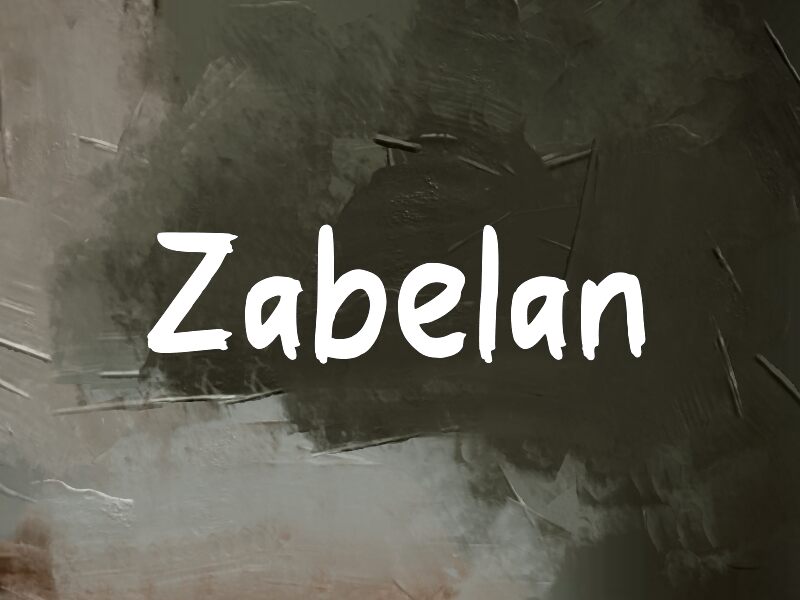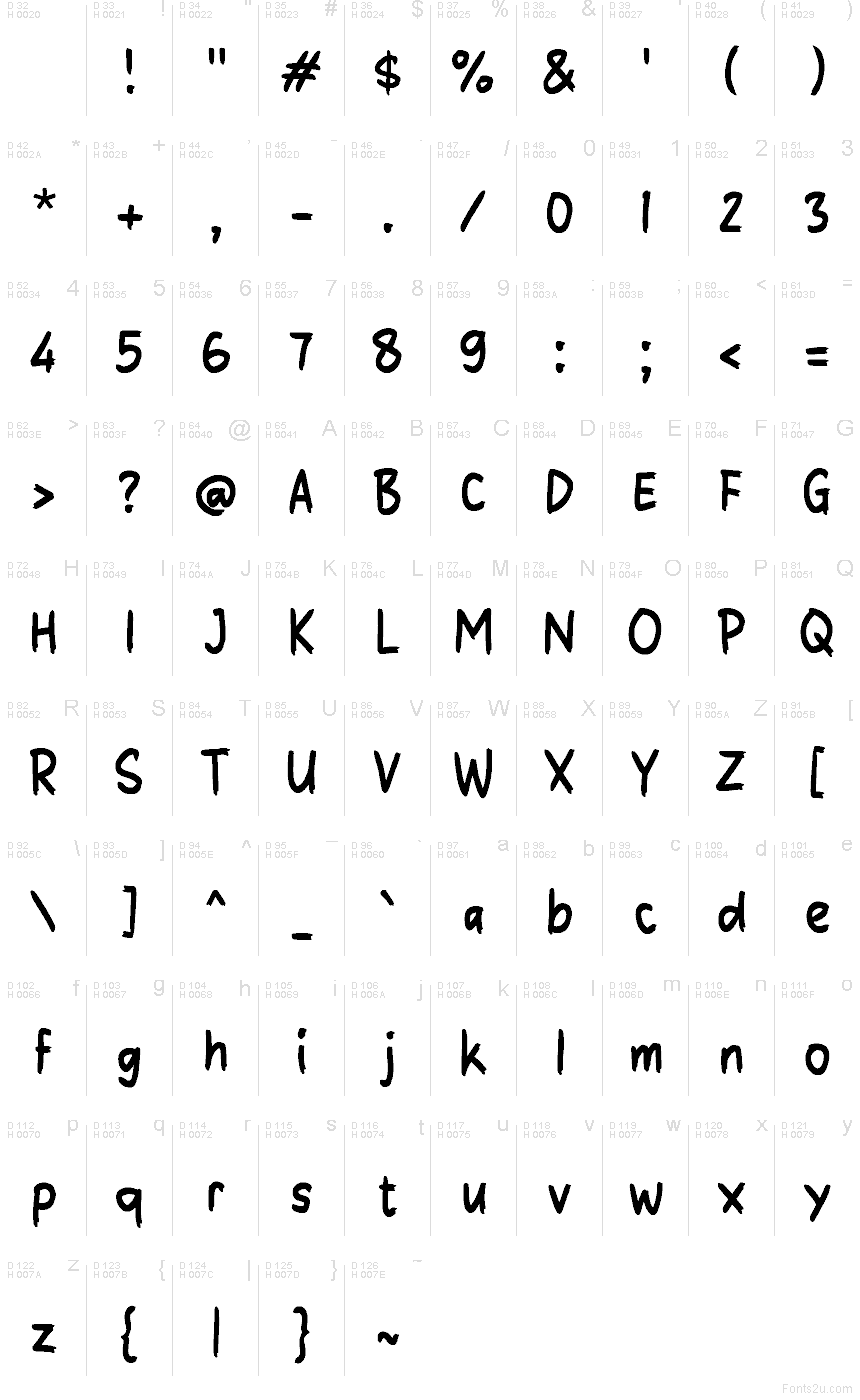
Zabelan
Zabelan od Wep je bezplatný brush font definovaný širokými ťahmi a rýchlym, vzpriameným rytmom. Písmená si zachovávajú ručne robený švih, s mierne nepravidelnými okrajmi a úzkymi spojmi, vďaka čomu pôsobia skôr ako nápis fixkou než ako uhladené písmo.
Táto autentická maliarska textúra dodáva krátkym titulkom na plagátoch, obaloch albumov, streetwearovej grafike, menu kaviarní či promo príspevkoch na sociálnych sieťach výrazný charakter. Je ideálnou voľbou pre obaly alebo letáky na podujatia, kde je svižný rukopisný prejav účinnejší než formálne a precízne písmo.